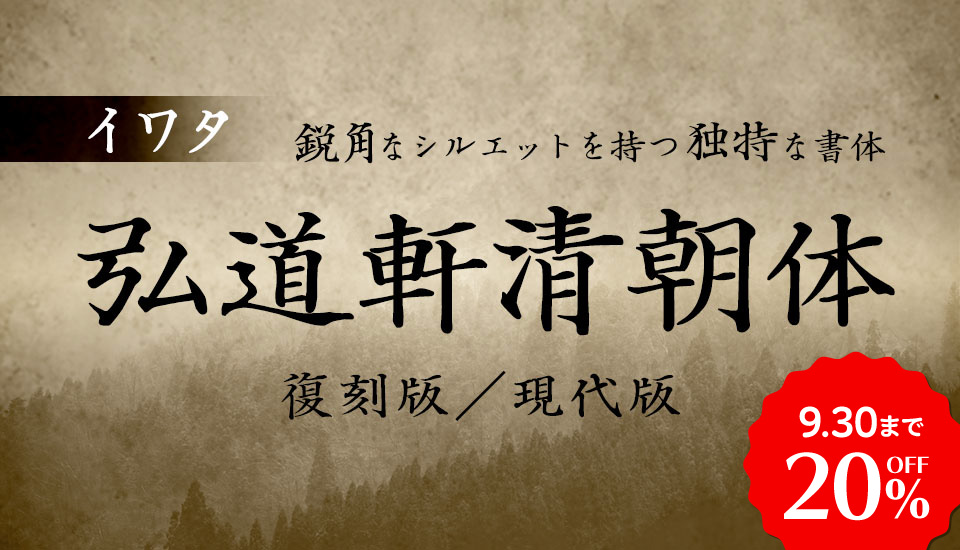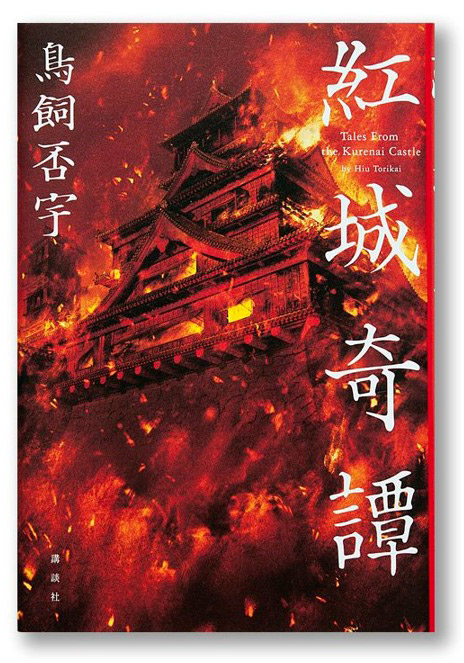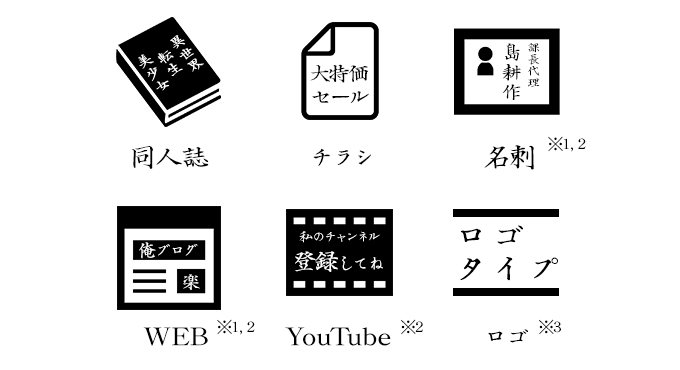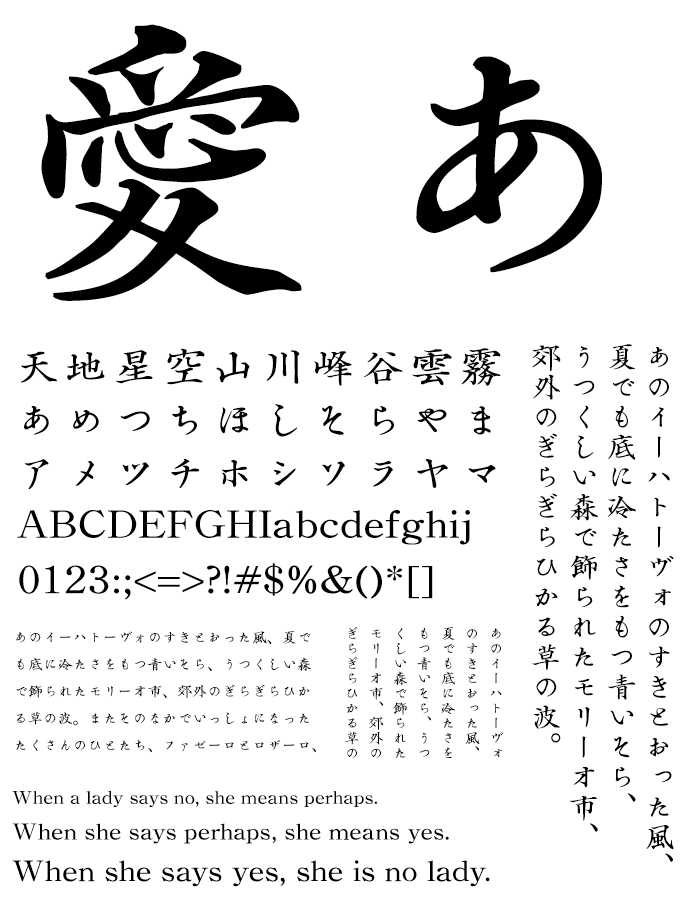
勝海舟も開発に一役買った『弘道軒清朝体』
「道軒清朝体」は、日本で一番古い部類の金属活字楷書体をデジタル化したフォントです。活字の父型は鋼鉄の角棒に文字を直彫りする豪快な手法で作成され、鋭角なシルエットを持つ独特な書体です。
その開発には勝海舟らの資金援助が大きな支えになり、10年に及ぶ歳月をかけ完成。完成後は東京日日新聞にも採用され、明治20年代にかけての流行書体として一世を風靡しました。
勝海舟からの資金で誕生した名書体
2017年に講談社から発売の『紅城奇譚』の表紙にも採用されています。
勝海舟も資金を出して完成した「弘道軒清朝体」。
独特な鋭角なシルエットと古風なイメージの「弘道軒清朝体」は、案内状、俳句、歌集などに合う雰囲気のある書体です。印刷物、同人誌、マンガ、YouTube、動画制作など、創作活動のあらゆる場面にご利用いただけます。
弘道軒清朝体の歴史
「弘道軒清朝体活字」は、明治7 (1874) 年に神崎正誼が創業した活版製造所「弘道軒」が、約10年をかけて開発しました。神崎正誼は薩摩出身で、初代東京赤坂区長を務め、大蔵省紙幣寮に勤務した経験を持つ実業家です。
この時代にはすでに金属活字を作る方法はできていましたが、神崎はその品質に飽き足らず、金属を直接彫るという新しい手法を採用しました。これにより「弘道軒清朝体」の特徴である鋭角なシルエットを持つ独特な書体が完成しました。
しかし、完成までには多くの困難がありました。特に資金面で苦労したといわれています。
全財産をつぎ込み途方に暮れていた神崎を助けたのは、同郷鹿児島出身の役人や、勝海舟らの資金援助でした。この援助が大きな支えになり、10年に及ぶ歳月をかけて完成。完成後は「東京日日新聞」にも採用され、明治20年代にかけての流行書体として一世を風靡しました。
活字はその後、昭和21年に「岩田母型製造所」の岩田百蔵が譲り受け、大切に保管されていました。これをベースにイワタがデジタルフォント化。2004年、『弘道軒清朝体 復刻版/現代版』として現代に復活させました。
弘道軒清朝体の特徴
弘道軒清朝体は、日本で一番古い部類の金属活字楷書体をデジタル化したフォントです。
清朝体は活字の号数によって字体や字画が異なりますが、イワタでは四号清朝体を基本にしています。
できる限りもとの字形を尊重して作成した「復刻版」と、古風なイメージを残しつつJISにほぼ準拠した「現代版」を同梱。「現代版」の仮名は「復刻版」より10%大きくデザインされています。
案内状、俳句、歌集などに合う雰囲気のある書体です。
※上記の組見本は「現代版」です。
現代版
復刻版
「現代版」の仮名は「復刻版」より10%大きくデザインされています。
現代版
復刻版